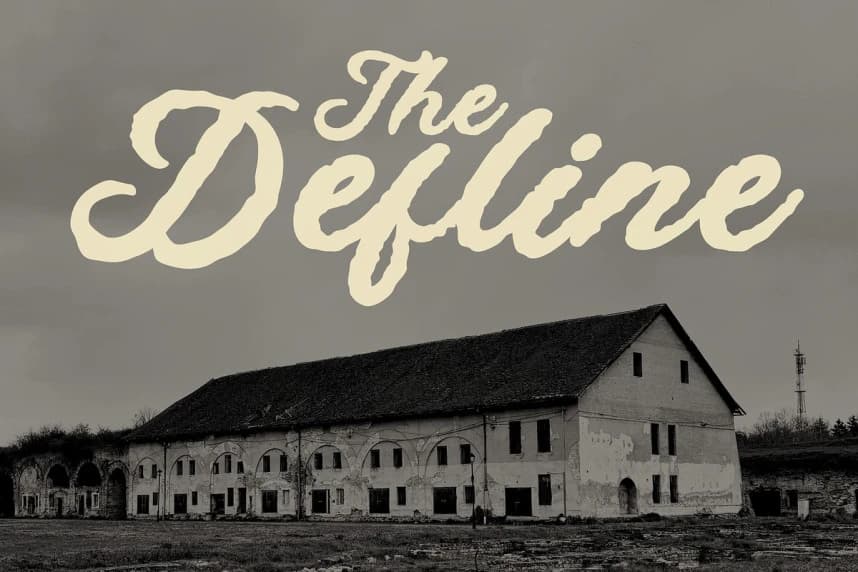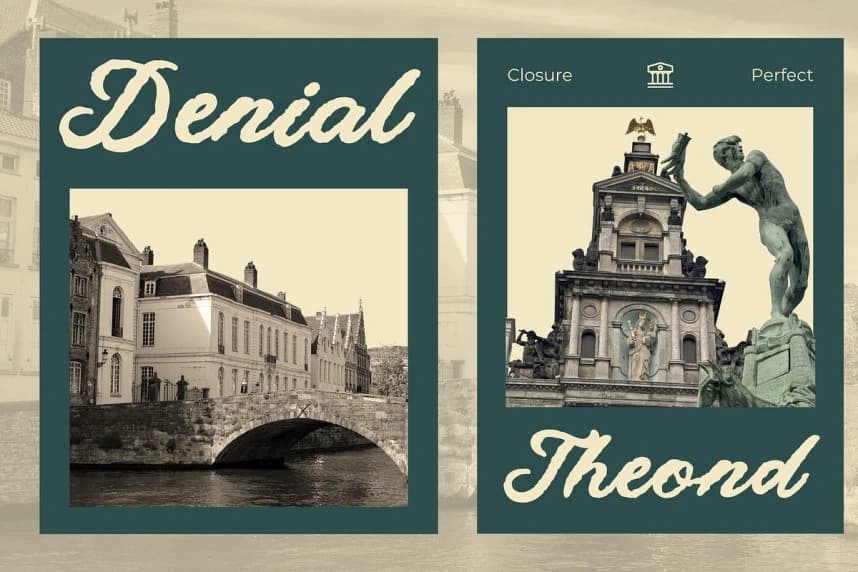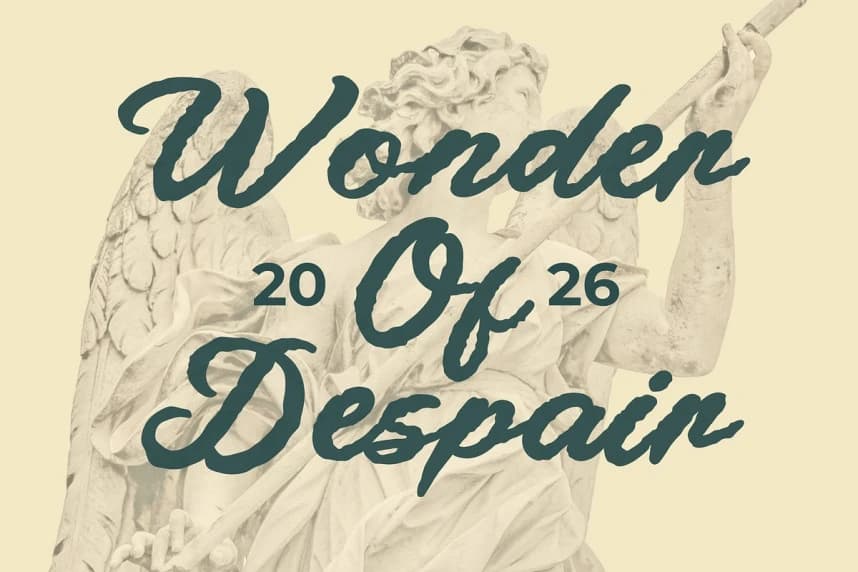
Fedley Script Font
Fedley Script Font, zarafet, akıcılık ve doğal el yazısı hissini bir araya veren modern bir kaligrafi yazı tipidir. Yumuşak akışkan kıvrımlar ve şık hatlarla tasarlanmıştır; bu yazı tipi herhangi bir tasarım projesine sofistike ve lüks bir dokunuş katar.
Fedley Script Font, zarafet, akışkanlık ve doğal el yazısı hissini bir araya getiren modern bir kaligrafi yazı tipidir. Akıcı eğriler ve şık çizgilerle tasarlanan bu yazı tipi, herhangi bir tasarım projesine sofistike ve lüks bir dokunuş katar.